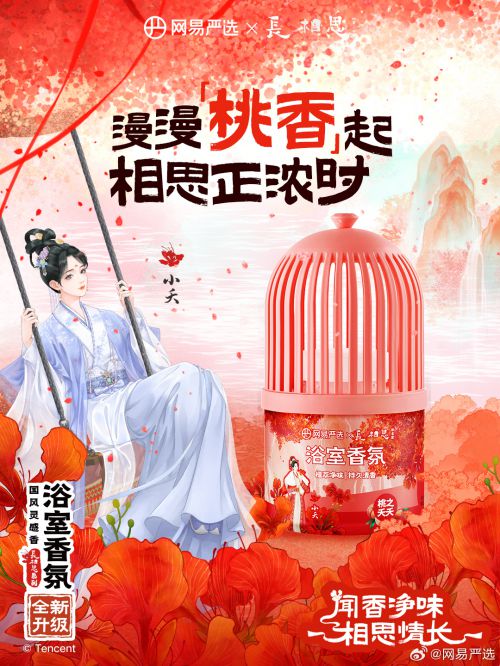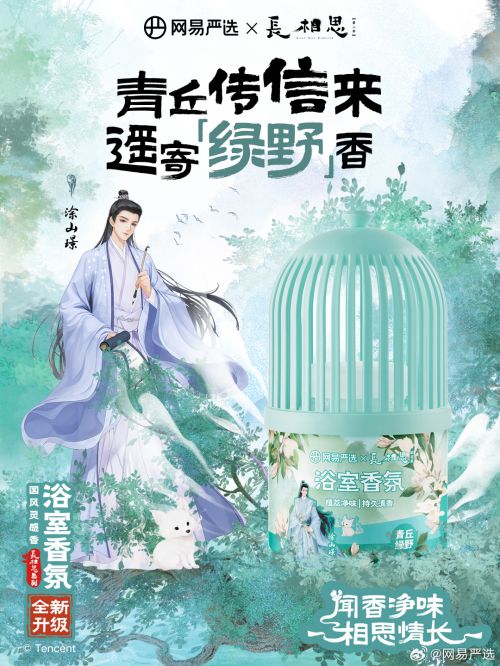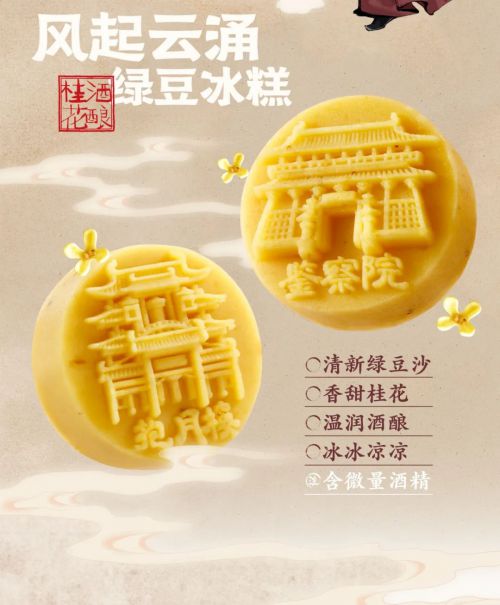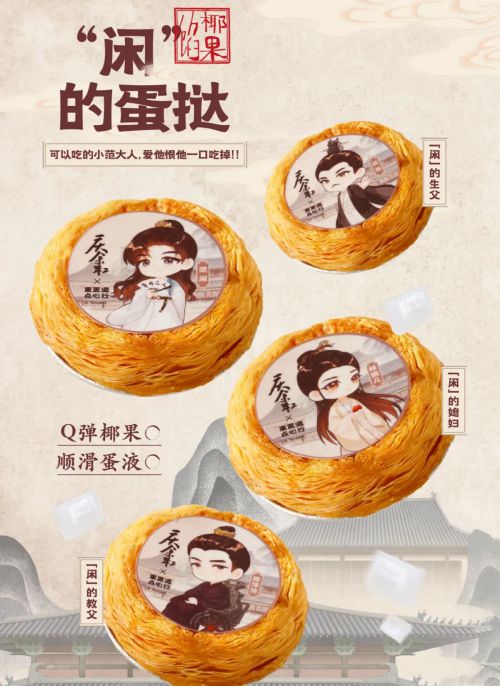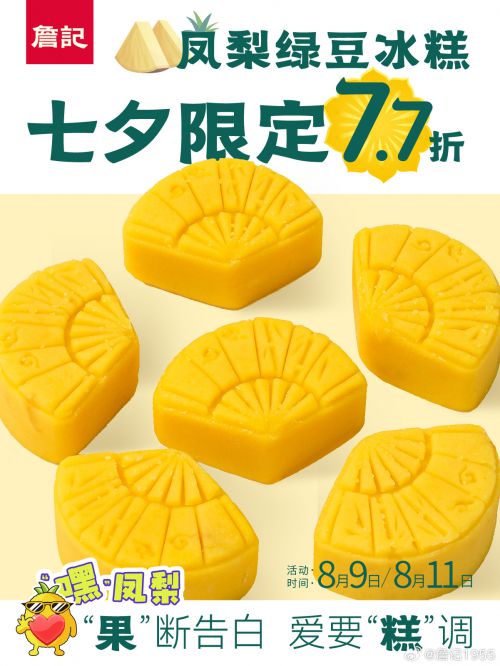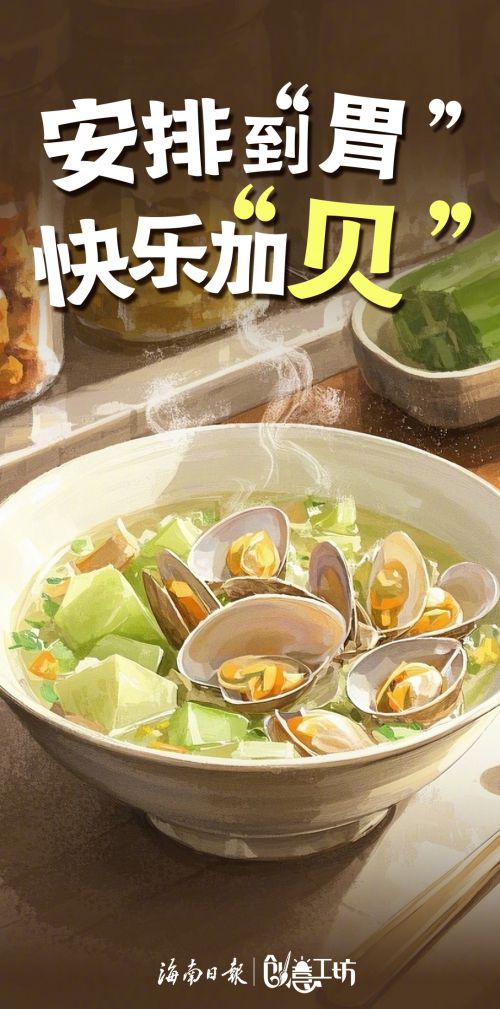
点字清逸隶是点字库精心打造的创意字体/黑体,以中国风古典美学为核心,融合复古韵味与现代设计智慧,兼具温和亲切的气质与端庄优雅的格调,会员可享商用授权,适用于多元设计场景。 点字清逸隶字形扁宽舒展,中宫宽博大气,重心稳健居中,尽显从容端庄之态。笔型巧妙融入斜切与装饰元素,方头笔画利落分明,粗细均匀中透着灵动;横竖线条飘逸舒展,转折处如刀刻般干净利落,既保留隶书的古朴骨架,又吸纳魏碑方笔的劲挺,让传统书法的韵味在现代排版中自然流淌。 作为兼具古典底蕴与实用价值的创意黑体,点字清逸隶无论是传统文创、品牌标识还是雅致文案排版,都能以复古而不失活力的视觉语言,传递温和亲切的情感与端庄优雅的文化质感,为设计注入独特的东方美学魅力。